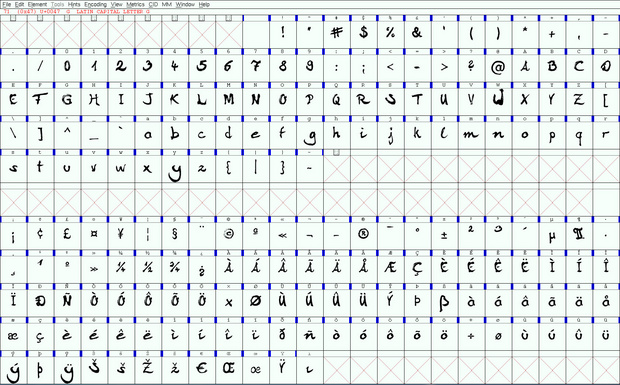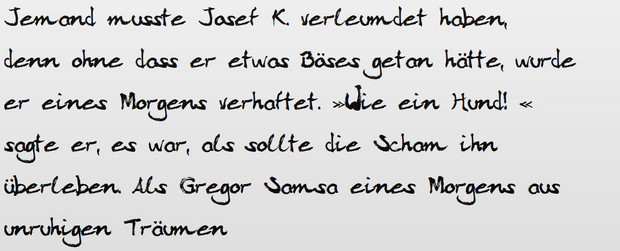
eigenen font für kommerziele zwecke erstellen.
ich bin momentan dabei eine eigene pinsel schrift zu erstellen mit dem ziel sie zum verkauf anzubieten.
dafür benutze ich einen scanner, illustrator und fontforge, mit letzterem bin ich jedoch euserst unerfahren.
was die glyphen betrifft sind schon einige fertig (groß und klein buchstaben A-Z sowie öäü und einige gängige sonderzeichen.), aber je weiter ich arbeite desto mehr fragen tun sich auf:
ich habe unter fontforge mit dem standard charakter set "latin-1" begonnen, jetzt fällt mir aber auf das dort z.b. das € zeichen garnicht vorhanden ist. gibt es eine norm die bestimmt welche glyphen mindestens vorhanden sein müssen um einen font kommerziel zu verkaufen?
ist es nötig bei schriften die warscheinlich nur für headlines genutzt werden, trotzdem großen aufwand fürs kerning zu betreiben um beim verkauf eine chance zu haben? (ich lese des öfteren das man bei headlines sowieso nochmal nachjustieren sollte.)
muss man von einem font immer gleich mehrere schriftschnitte anfertigen um kommerziele erfolgs chancen zu haben? (ist bei einem hand gefertigem pinsel font doch recht schwierig und aufwändig ihn dünner, dicker, kursiv... nochmal zu zeichnen und dabei trotzdem den charakter des originals einzuhalten. und einfach nur im illustrator die schrift zu verzerren kann ja nicht die lösung sein, oder ist das so gängig?)
ist es mit fontforge möglich für einen charakter zwei verschiedene glyphen zu bestimmen? also z.b. für den charkter kleines m einen glyph der innerhalb eines wortes benutzt wird und einen glyph der nur eingesetzt wird wenn das m der letzte buchstabe eines wortes ist?
welches format sollte ich wählen, truetype oder opentype?
und schlussendlich wo kann man so einen font überhaupt anbieten? auf größeren seiten wie linotype oder fontshop konnte ich dazu nichts finden und auf meine e-mail bekomme ich keine antwort.
Ich kann dazu nur aus Nutzer/Kundensicht antworten.
Wenn sie gut gemacht ist, dann braucht die Schrift für Displayzwecke nicht unbedingt mehr als einen Schnitt. Gerade wenn du eine Hand- oder Pinselschrift anbieten willst, ist es fast schon notwendig, kontextabhängige Glyphen („m“) und Ligaturen anzubieten, damit es wie in einem Zug geschrieben aussehen kann. Dazu brauchst du eine OpenType-Schrift. Und dann hast du auch keine wirkliche Begrenzung der Zeichenzahl. Auf das Kerning würde ich auch Wert legen. Eine Schrift, bei der ich alles nochmal von Hand nachbearbeiten muss motiviert nicht gerade. Ein € ist auf jeden Fall notwendig, wenn du hierzulande eine Chance haben willst. Die west- und mitteleuropäischen Zeichen solltest du schon abdecken. Verkaufen kannst du das dann über myfonts.com.
Was man alles machen MUSS ist nicht die Frage. Die Frage ist, welche Merkmale und welche Qualität dein Font für Dich und Deine Kunden haben SOLL. Das kannst aber nur du entscheiden. Und nicht alles was möglich ist, ist auch sinnvoll oder wird entsprechend nachgefragt. Diese Entscheidungen kann Dir keiner abnehmen.
Zu den technischen Fragen:
Für lateinische Schriften ist eine komplette Latin1-Belegung in der Tat der Standard. Latin 1 wurde definiert, bevor es den Euro gab. Dieser ist deshalb in ISO 8859-15 drin http://de.wikipedia.org/wiki/ISO_8859-15
Ein End-m zusätzlich zu einem normalen m kannst in FontForge über OpenType-Features einrichten. Ist aber vielleicht für einen Anfänger nicht ganz einfach.
TrueType oder OpenType? Ist eigentlich egal. Wenn du den Font mit PostScript-Outlines entwirfst, bietet es sich an, einen PostScript-basierten OpenType-Font zu verkaufen – dann muss nichts konvertiert werden.
Der Verkauf über MyFonts ist am einfachsten und schnellsten. Du musst den Font quasi nur hochladen. Alternativ kannst du auch ein echter FontFont-Designer, Linotype-Designer usw. werden. Das geht aber nicht von heute auf morgen. Dein Font wird entsprechend begutachtet und du bekommst technische Qualitätsrichtlinien, die du einhalten musst, bevor der Font wirklich verkauft wird. Das zieht sich entsprechend und die Hürde ist hier für Anfänger deutlich höher.